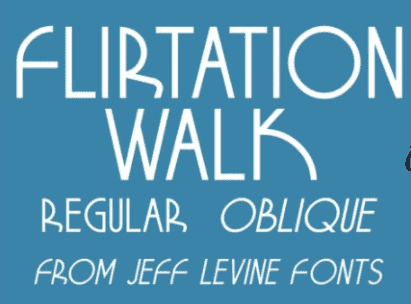
Название: Flirtation Walk Font (2021)
Шрифт Flirtation Walk JNL был вдохновлен надписями на обложках нот для песен, взятых из фильма 1934 года с Диком Пауэллом и Руби Килер "Flirtation Walk".
Шрифт содержит стилизованные символы, а также более привычные символы ар-деко и доступен в обычном и наклонном вариантах.